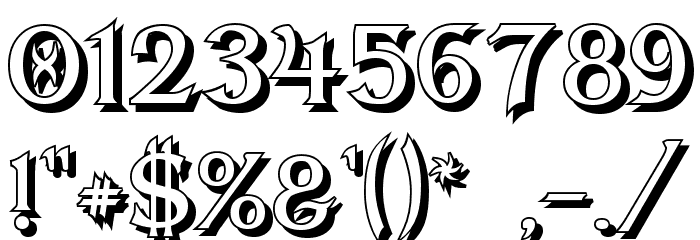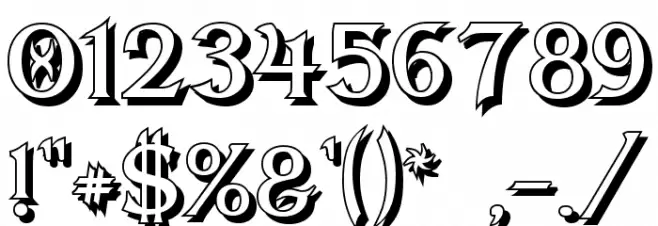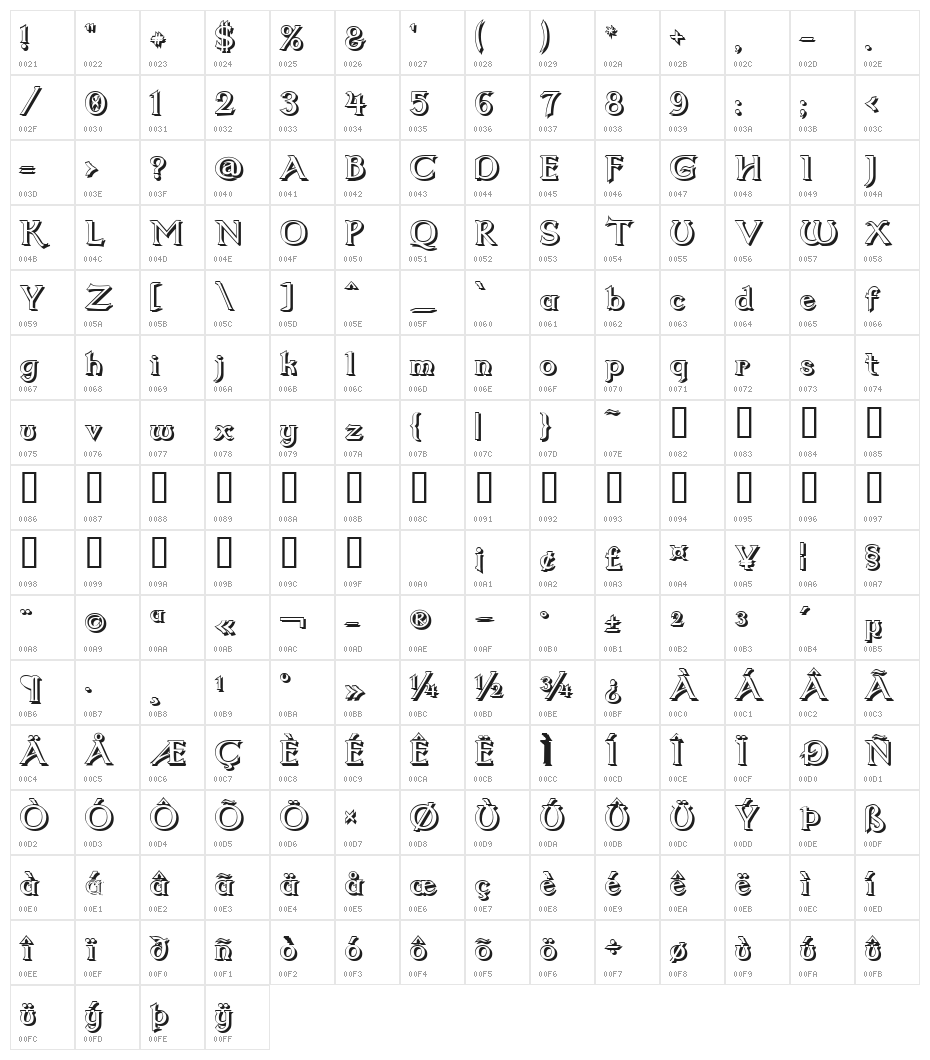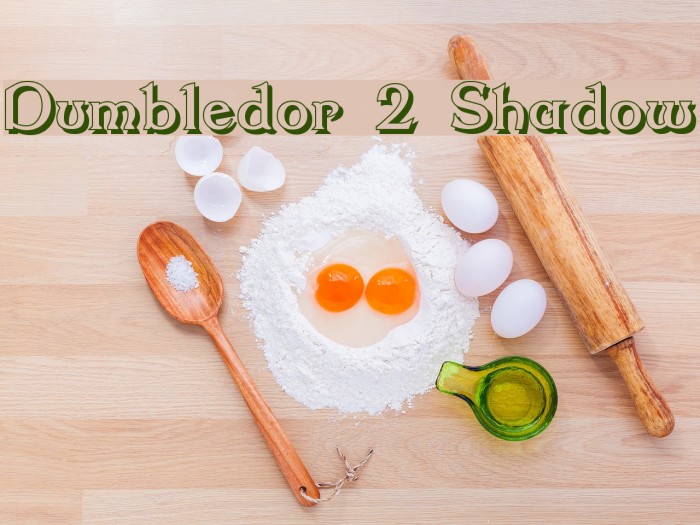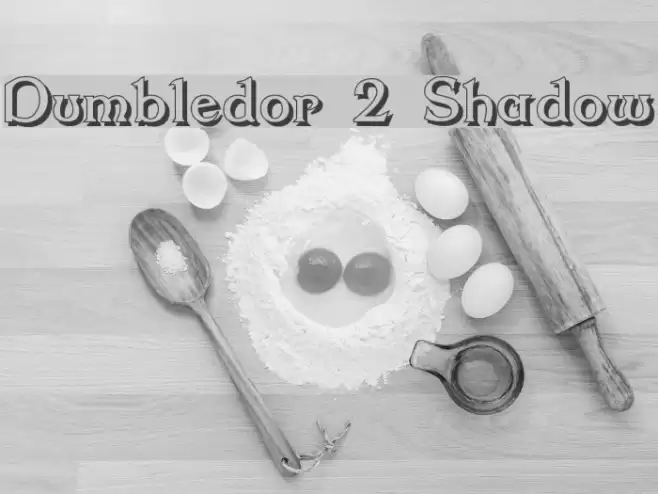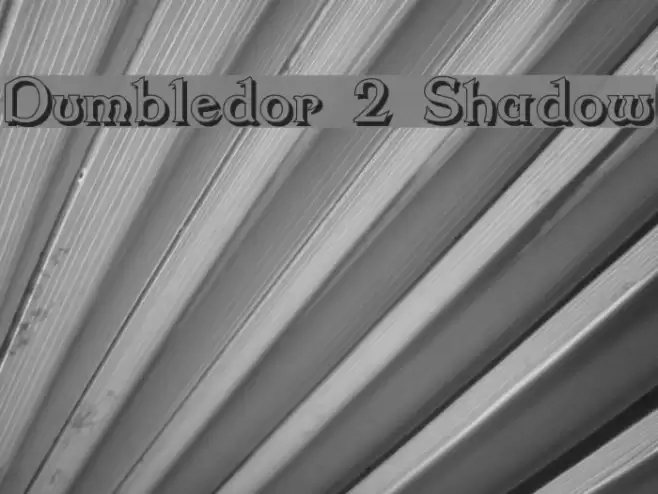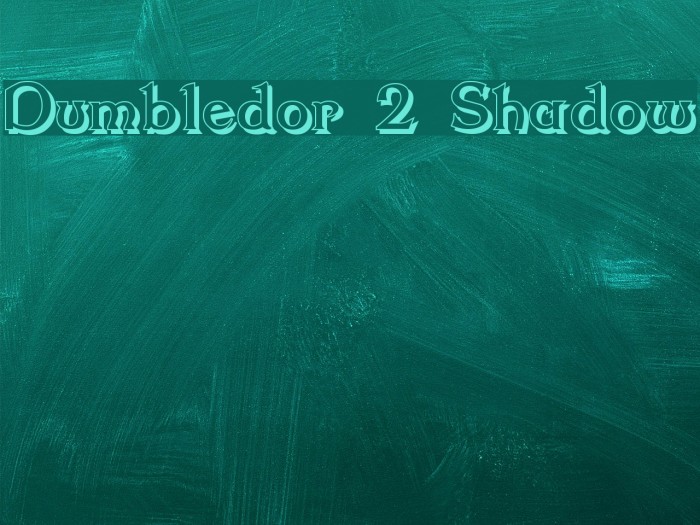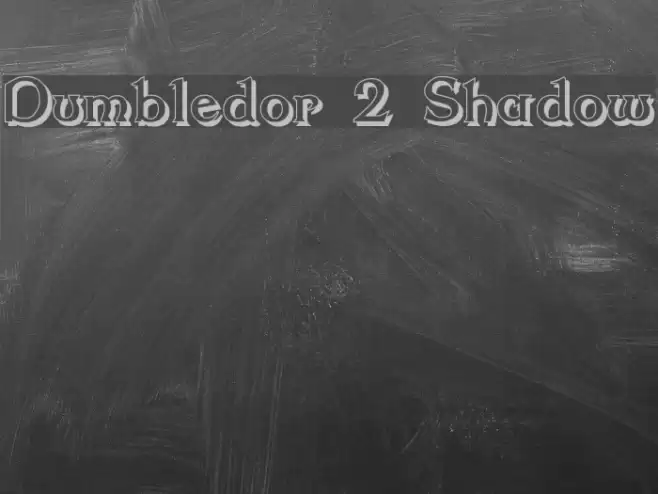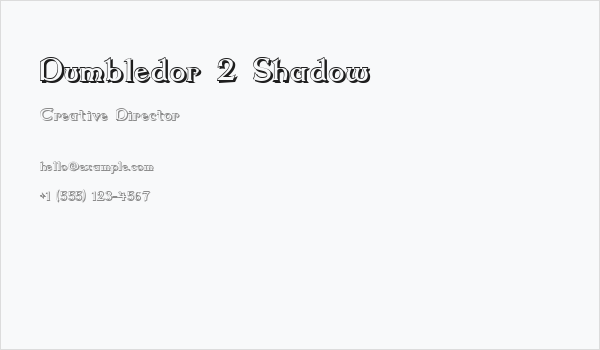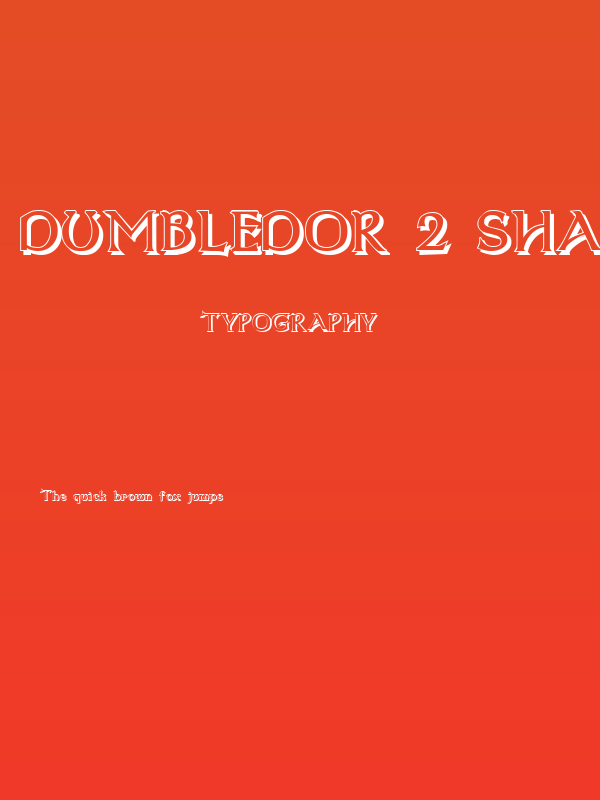
Dumbledor 2 Shadow Font
✎ Gothic
| नाम | Dumbledor 2 Shadow |
| श्रेणियाँ | Gothic |
| कंट्रास्ट | High |
| समग्र शैली | Vintage, Dramatic |
| उपयोग का मामला | Headlines, Logos, Posters |
| सुझाए गए प्रोजेक्ट | Suitable for book covers, movie posters, fantasy-themed events, and branding that requires a bold statement. |